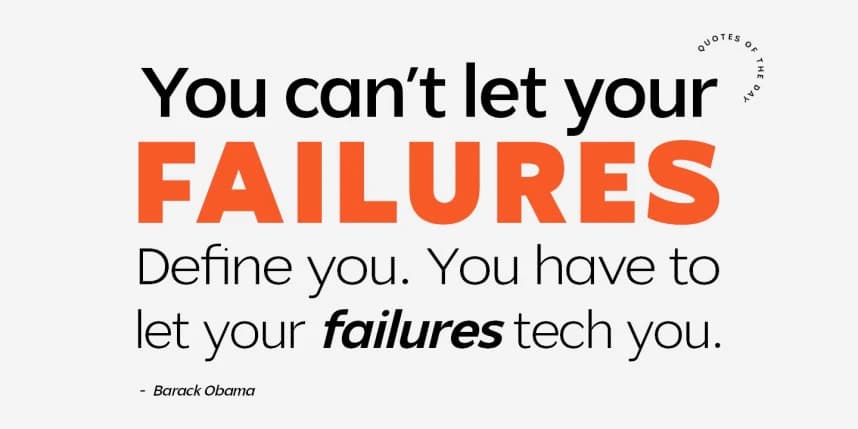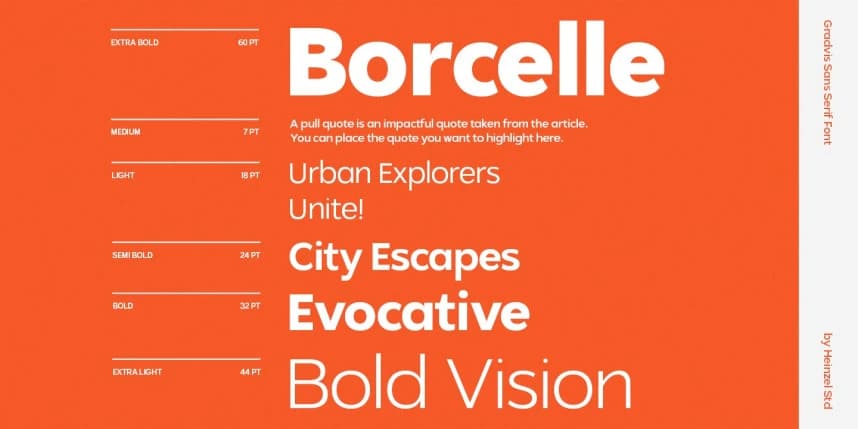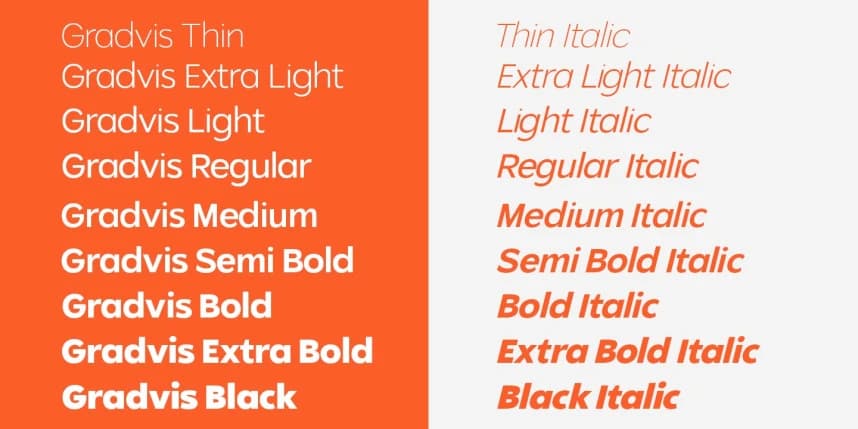
Gradvis Font
Gradvis Font, herhangi bir projeye netlik, esneklik ve çağdaş stil kazandırmak amacıyla tasarlanmış modern ve çok yönlü bir sans-serif yazı tipidir. Hassasiyetle ve temiz bir geometrik yapı ile tasarlanan Gradvis, dijital ve basılı medyada kusursuz çalışan akıcı bir görsel akış sunar.
Gradvis Font, netlik, esneklik ve çağdaş tarzı herhangi bir projeye kazandırmak için tasarlanmış, modern ve çok yönlü bir sans-serif yazı tipidir. Netlik ve temiz geometrik bir yapı ile tasarlanan Gradvis Font, dijital ve baskı medyada sorunsuz bir görsel akış sağlar.